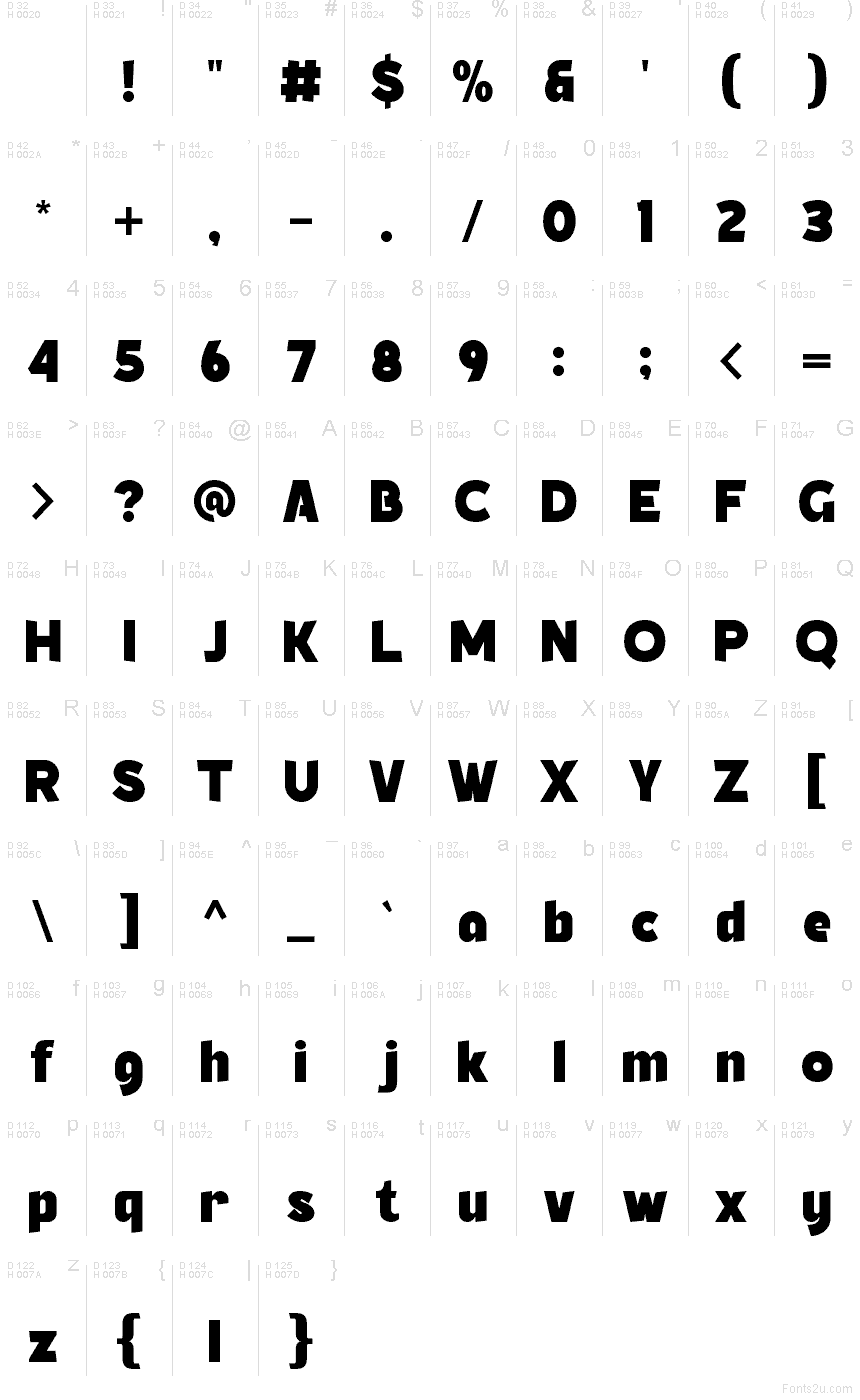
Traven od Ermedia Studio je bezplatné retro display písmo s velmi silnými tahy a širokými, těsně sázenými literami. Šikmé zářezy narušují jinak celistvé siluety. Drobné vnitřní prostory a plné křivky dodávají nápisům až přetékající dojem, zatímco ostré hrany vytvářejí lehce nevšední zakončení.
Retro reklama představuje pro tento hutný nápis přesvědčivé prostředí, zejména na obalech potravin a propagačních plakátech, kde jeho tvary mohou evokovat hojnost. Hodí se také pro vizuální styl bister a dinerů, kde jeho mohutné křivky a ostře řezané hrany přirozeně navozují veselý, naddimenzovaný vzhled ručně malovaných vývěsních štítů.